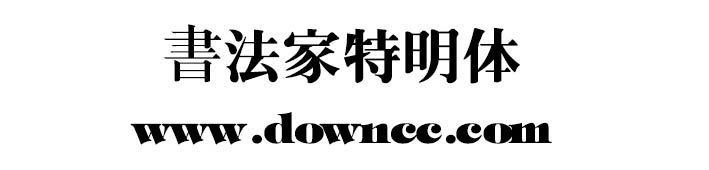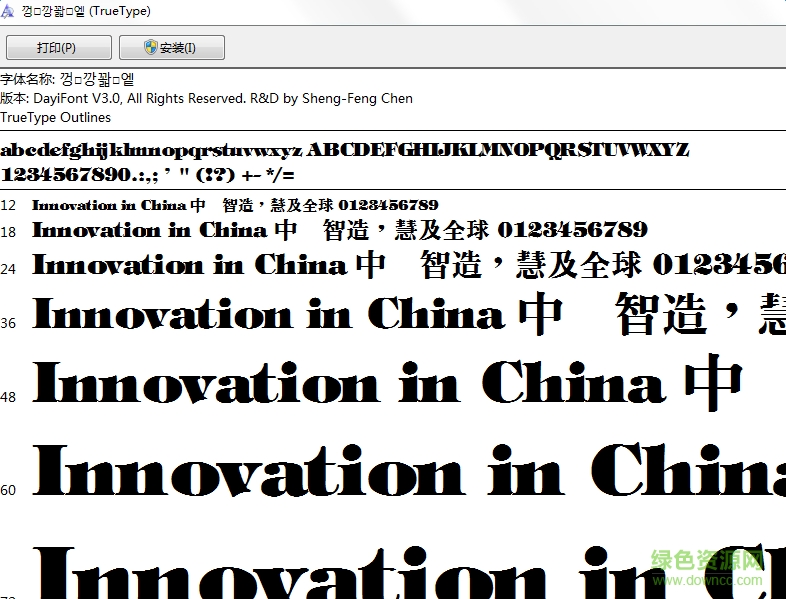
書法家特明體字體是一款藝術(shù)設(shè)計類書法字體,采用中文傳統(tǒng)字體打造而成,喜歡的親,可以直接下載安裝即可使用,喜歡就來綠色資源網(wǎng)下載體驗唄!
書法家特明體是一款應用于藝術(shù)設(shè)計方面的簡體中文漢字,該字體端正大方,一筆一畫規(guī)規(guī)矩矩,整體效果非常出眾,能夠適用于包裝印刷、廣告設(shè)計、平面設(shè)計、書籍報紙等領(lǐng)域,喜歡的朋友快下載收藏吧。